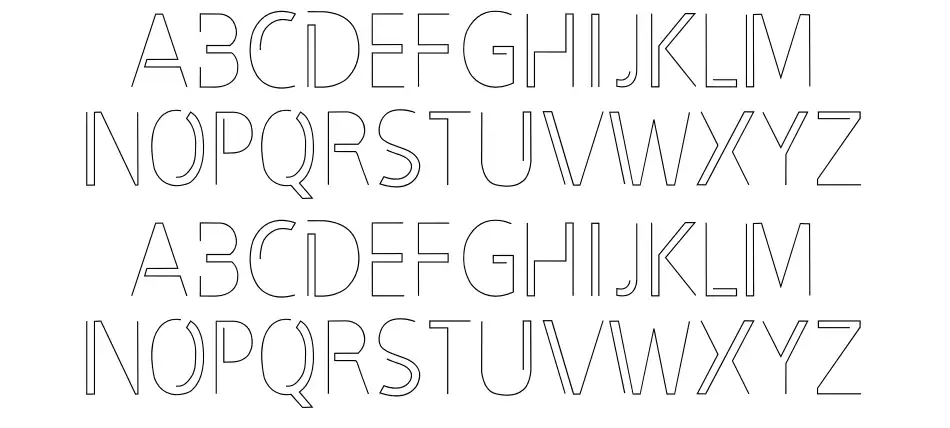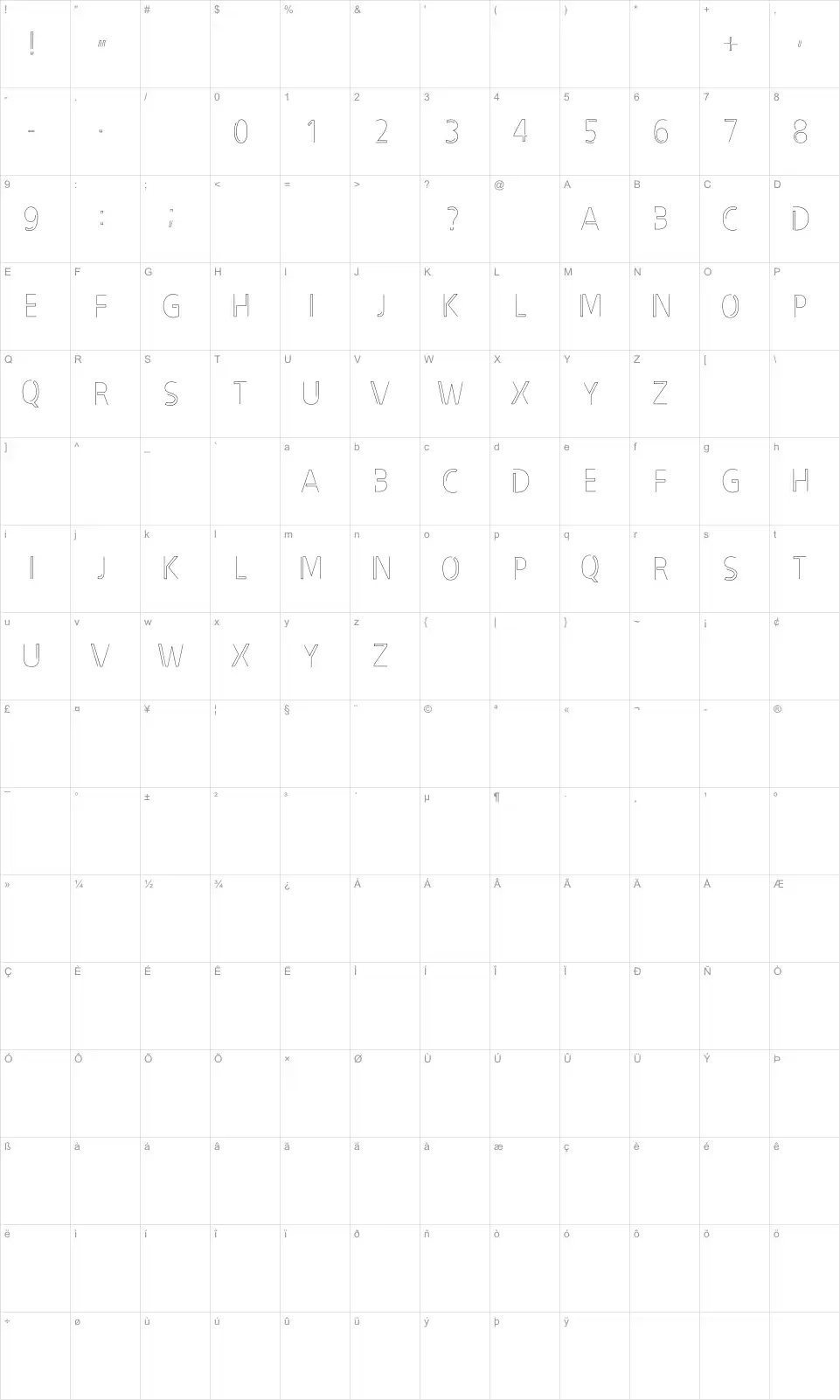
Filament font – Download Grátis
A fonte ‘Filament’ é perfeitamente adequada para criadores de conteúdo que buscam um estilo casual e criativo para seus materiais. Desenhada por Andrea Deinert, esta fonte pertence à categoria Fancy e é versátil o suficiente para uso em diversos projetos. Se você está procurando por esta fonte, está no lugar certo. Pode baixá-la ou gerar um previsual personalizado do texto online para ver como ela ficará antes de começar a usar. Licenciada para uso pessoal e disponível em formato TTF, a fonte ‘Filament’ foi adicionada em 12 de julho de 2022 e já teve 1784 downloads. Seu tamanho compacto de 6 KB a torna conveniente e fácil de integrar em qualquer projeto.